Helvetica er en skrifttype, der i årtier har været en hjørnesten i designverdenen. Dens rene, neutrale og yderst læsbare design har gjort den til et foretrukket valg for alt fra firmalogoer til brugergrænseflader. Men med den nylige udfasning af Type 1-skrifttyper i Adobe Creative Cloud står mange brugere, der har investeret i denne teknologi siden slutningen af 80'erne, over for en udfordring: Hvor finder man passende alternativer, når ens betalte, gamle skrifttyper pludselig er ubrugelige?
Dette skifte kan føles frustrerende, især for dem, der har brugt Type 1-skrifttyper i årevis. Det er dog et faktum, at industrien bevæger sig mod mere moderne og alsidige formater som OpenType. Adobe har taget skridtet fuldt ud, og ja, du kan roligt antage, at dine gamle Type 1-skrifttyper er blevet fjernet fra dit Creative Cloud-dashboard. Dette er en del af overgangen og ikke en fejl.
Spørgsmålet melder sig så: Hvilke skrifttyper kan erstatte Helvetica, især familier som Helvetica Neue Condensed, og findes der gode alternativer inkluderet i Creative Cloud-abonnementet?
Hvorfor søge alternativer til Helvetica?
Ud over nødvendigheden på grund af Type 1-udfasningen kan der være mange grunde til at søge alternativer til Helvetica. Måske leder du efter noget med en lidt anden personlighed, en skrifttype der er bedre optimeret til skærme, eller simpelthen et gratis alternativer til kommerciel brug. Heldigvis findes der et væld af højkvalitets skrifttyper, der deler mange af Helveticas karakteristika – dens klarhed, neutralitet og gode læsbarhed – men som tilbyder deres egne unikke fordele.
Alternativer inden for Adobe Creative Cloud (Adobe Fonts)
Dit Creative Cloud-abonnement giver adgang til et stort bibliotek af skrifttyper via Adobe Fonts. Selvom en direkte, gratis klon af Helvetica Neue Condensed muligvis ikke er navngivet præcis sådan, indeholder biblioteket mange neo-groteske skrifttyper, der deler æstetiske ligheder og kan fungere som fremragende erstatninger. For eksempel findes der en mere omfattende version af Nimbus Sans (diskuteret nedenfor) med flere vægte og indstillinger for bredde og kondensering, som er tilgængelig via Adobe Fonts. Det er værd at udforske biblioteket med søgetermer som "sans-serif", "grotesque" eller "neo-grotesque" for at finde skrifttyper, der passer til dit behov for en neutral, men effektiv visuel stemme.
Populære gratis alternativer til Helvetica
Hvis du leder efter gratis alternativer af høj kvalitet, der kan bruges i Photoshop, InDesign og andre programmer, er der flere fremragende muligheder. Disse er ofte tilgængelige via platforme som Google Fonts eller Font Squirrel.
1. Inter
Designet af Rasmus Andersson, Inter er et fantastisk open source-alternativ, der er optimeret til skærmbrug. Den har generelt mere generøs afstand end Helvetica, hvilket gør den velegnet til UI-design. Selvom dens terminaler (ende-stykkerne på bogstaver) ikke er så strengt vandrette eller lodrette som Helveticas, hvilket giver Helvetica et meget skarpt udseende, er Inter til gengæld ofte mere læselig ved små størrelser. Inter tilbyder 9 vægte plus kursiv og er også tilgængelig som en variabel skrifttype. Findes på Google Fonts.
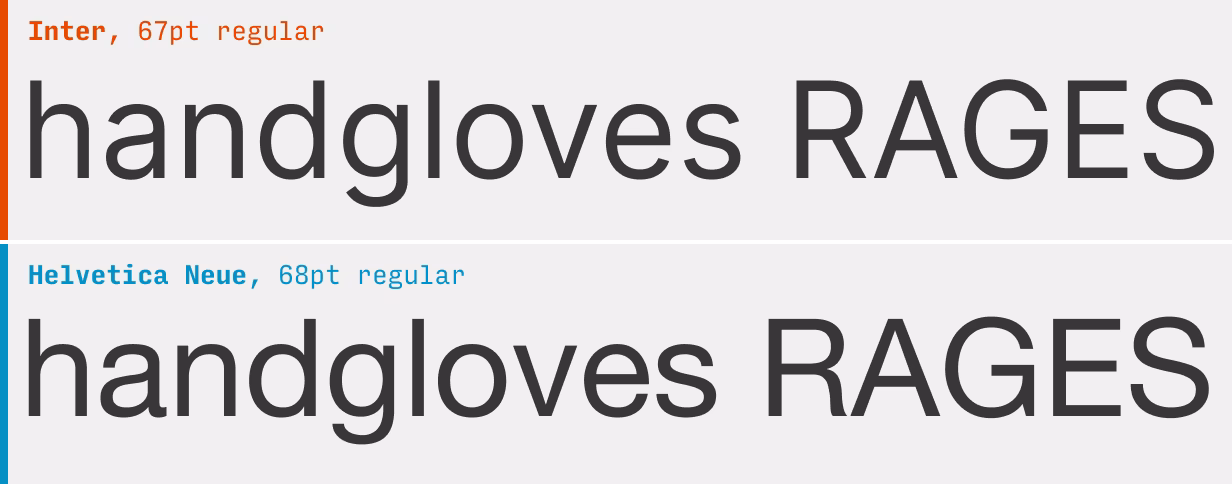
2. Roboto
Robot er standardskrifttypen på Android og er gratis at bruge. Selvom den ikke er en nøjagtig kopi af Helvetica, er det en anden robust sans-serif, der passer ind i samme kategori. Robot har lidt tyndere og mere kompakte bogstavformer, hvilket kan være en fordel, hvor plads er kritisk. Ved brug på web kan man endda ændre udseendet på visse tegn (f.eks. et mere Helvetica-lignende "R") via CSS. Roboto har 6 vægte plus kursiv. Findes på Google Fonts.
3. Arimo
Arimo, designet af Steve Mattheson, var oprindeligt tænkt som en frisk version af Arial, men fungerer glimrende som en erstatning på tværs af platforme. Den har lidt højere bogstavformer end Helvetica, men er ellers en solid erstatning. Vær opmærksom på, at Arimo ikke har lettere vægte end den normale vægt. Arimo tilbyder 4 vægte plus kursiv og er også tilgængelig som en variabel skrifttype. Findes på Google Fonts.
4. Nimbus Sans
Designet af URW, Nimbus Sans er et fantastisk alternativ, der direkte er baseret på Helvetica. Den matcher mange af Helveticas karakteristiske træk, såsom de vandrette og lodrette terminaler og formen på visse bogstaver. En mærkbar forskel er, at Nimbus Sans ofte er mørkere, hvilket betyder, at bogstavformerne er tykkere ved en given størrelse. Den gratis version har 2 vægte plus kursiv og kan findes på Font Squirrel. Som nævnt er en mere omfattende version tilgængelig via Adobe Fonts.
5. TeX Gyre Heros
TeX Gyre Heros bygger på Nimbus Sans og er derfor meget tæt på Helvetica. Den inkluderer et par mindre forbedringer, men er i bund og grund en næsten identisk match. Hvis du kun har brug for to vægte, dækker denne skrifttype dit behov. Den har 2 vægte plus kursiv og en kondenseret indstilling (også 2 vægte). Findes på Font Squirrel.
6. Work Sans
Work Sans af Wei Huang er et godt valg, hvis du ønsker en anelse mere personlighed. Det er en venligere grotesk med en mere afslappet afstand og små, unikke detaljer i bogstavformerne. Den tilbyder 9 vægte plus kursiv og er tilgængelig som en variabel skrifttype. Findes på Google Fonts.